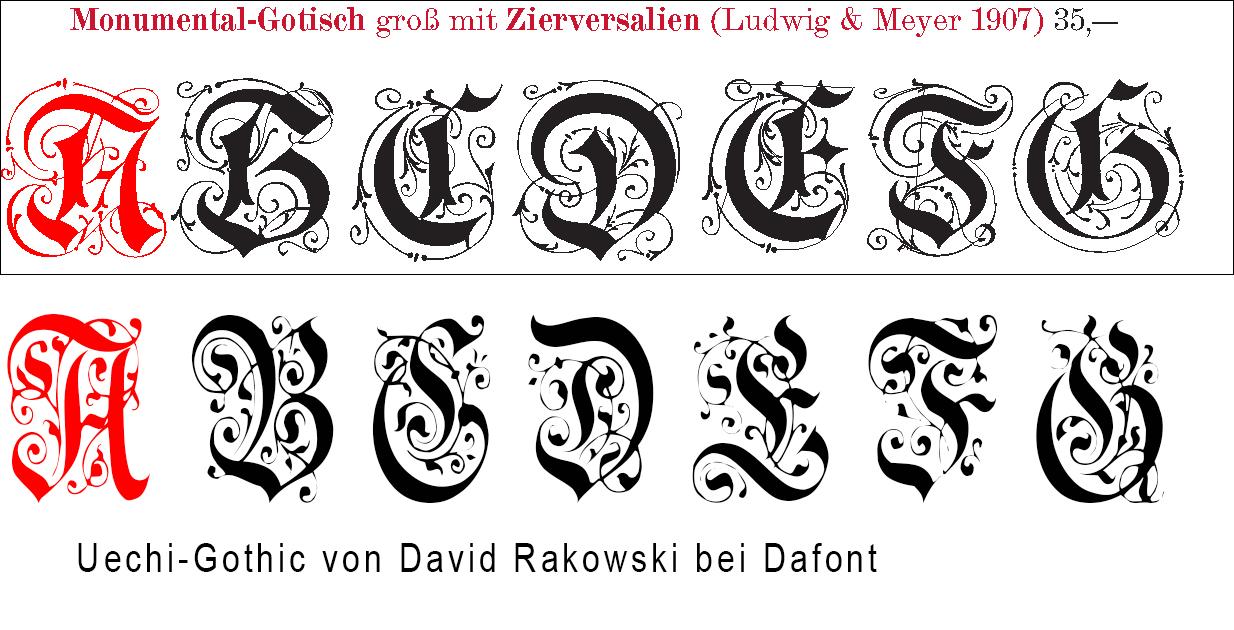
Suche Schriftart dieses Logos (Wappen-Grafik)
auf der Webseite www.wappen grafik atelier.net habe ich diese Schrift gefunden. Im Zusammenhang mit einer Wappenerstellung suche ich diese oder ähnliche. Mir kommt es vor allen Dingen auf die Verzierung des jeweils ersten Buchstaben an. Wer kann helfen. Wenn es etwas kostet ist auch kein Problem. Das Wappen welches ich nacharbeiten will stammt aus dem 17/18 Jh.
Helzel hat nicht nur "unendlich" viele gebrochene Schriften, sondern sogar Multi-Layer-Fonts: www.romana-hamburg.de
Die Versalien könnten aus der Renaissance Kanzlei stammen (Renaissance-Kanzlei groß 60 Pkt. (Berthold, Bauer & Co. Stuttgart, Breitkopf & Härtel). Die kannst du – wie Phoibos ja bereits gesagt hat – bei Herrn Helzel beziehen.
Warum in die Ferne schweifen.... Da habe ich einfach in diesem Atelier angerufen und der Chef war so nett mir den Schriftnamen zu verraten.
Es handelt sich um die Schriftart Uechi-Gothik. Bei Hertel habe, auf Grund der Ratschläge hier, eine ähnliche gefunden: "Monumental-Gotisch groß mit Zierversalien" von Ludwig und Meyer von 1907 für 35.-€. Danke an alle die mitgemacht haben.